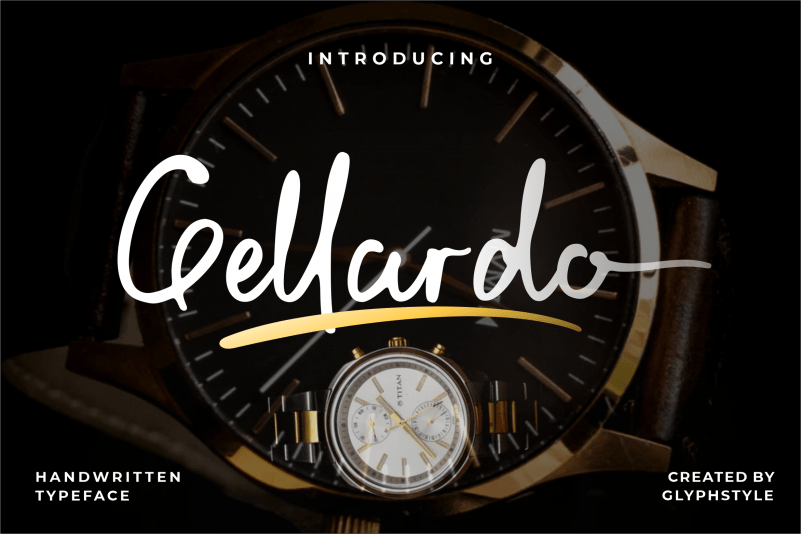
Gellardo Handwritten Typeface – Download Grátis
A Fonte ‘Gellardo Handwritten Typeface’ é uma obra-prima para designers que buscam um estilo elegante e autêntico no design editorial ou em projetos visuais pessoais. Esta tipografia original, criada pelo Designer GlyphStyle, oferece linhas suaves e textura naturais com traços perfeitamente balanceados, tornando-a ideal tanto para gráficos profissionais quanto para trabalhos de arte digital e artesanais. As curvas suaves e as nuances da escrita acentuada fazem dela uma opção segura para qualquer projeto que valorize um toque pessoal e descontraído. Seja para criar cartazes, infográficos ou até mesmo páginas web responsivas, ‘Gellardo Handwritten’ não decepcionará em oferecer uma experiência visual inovadora e agradável aos olhos dos usuários.